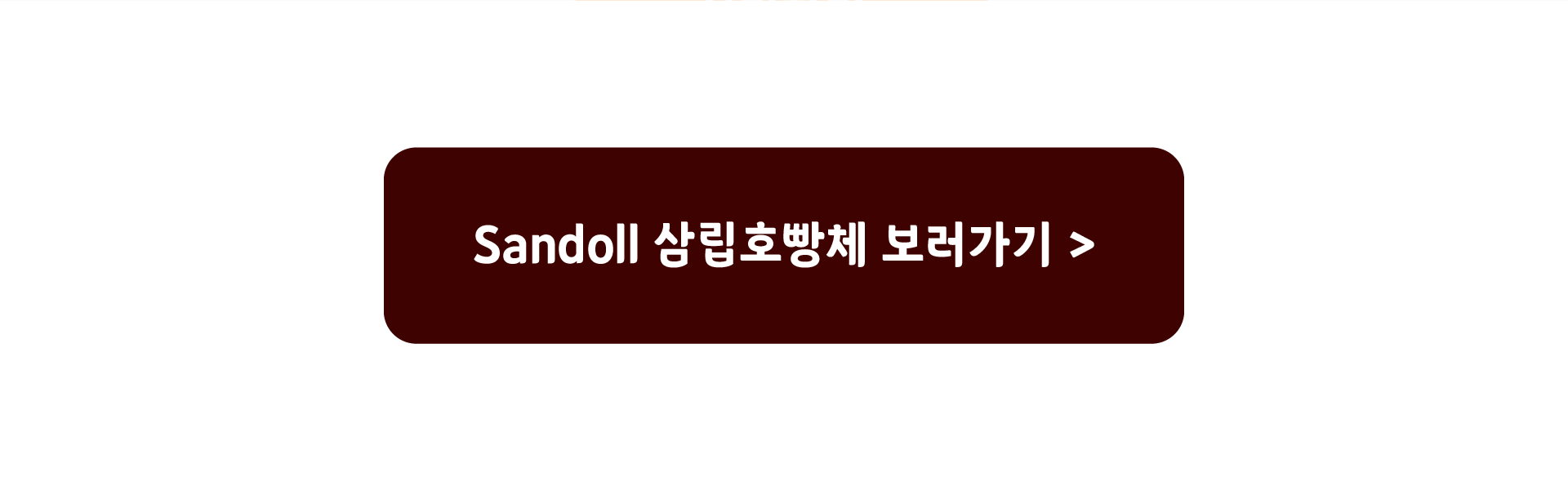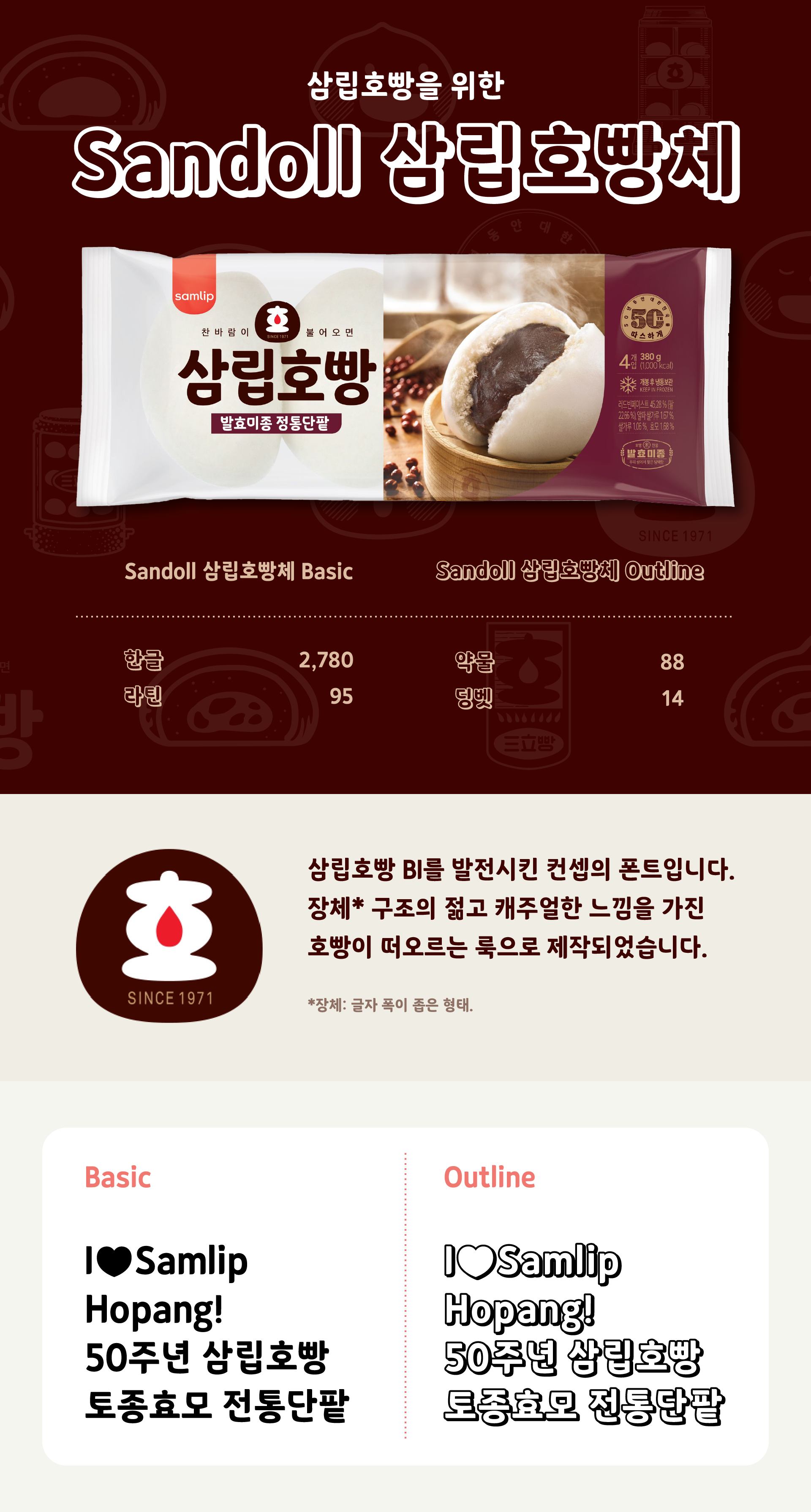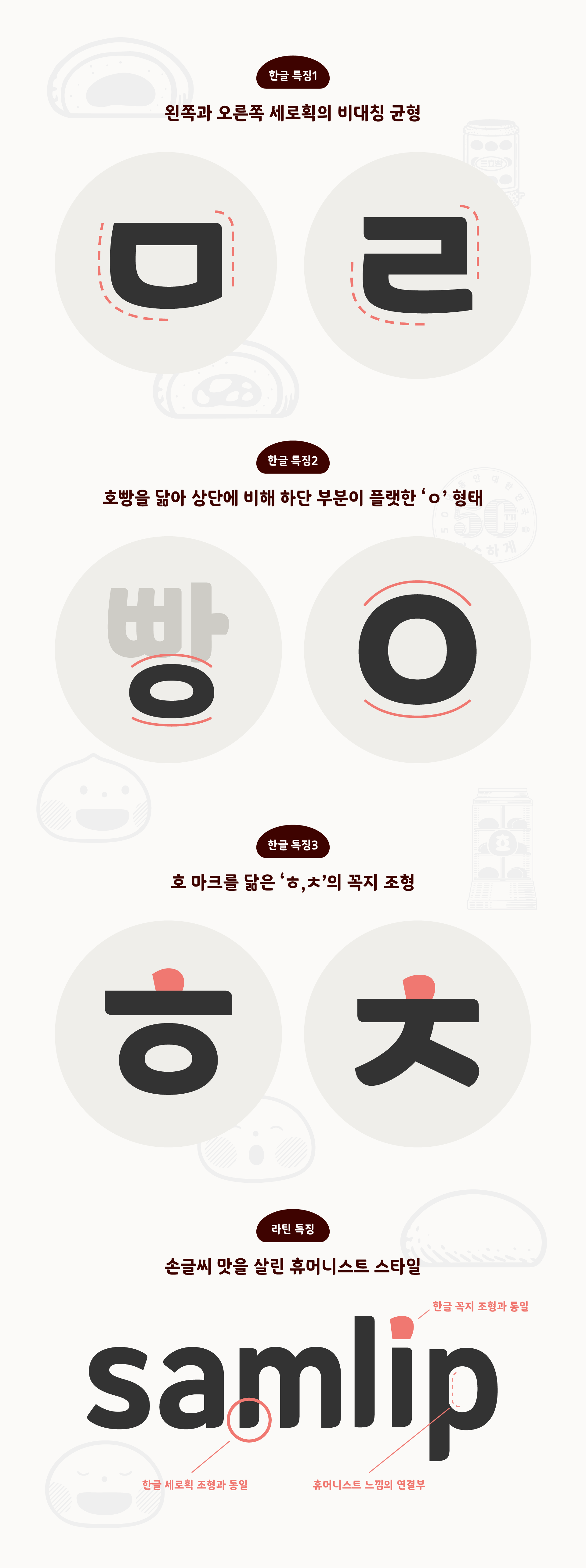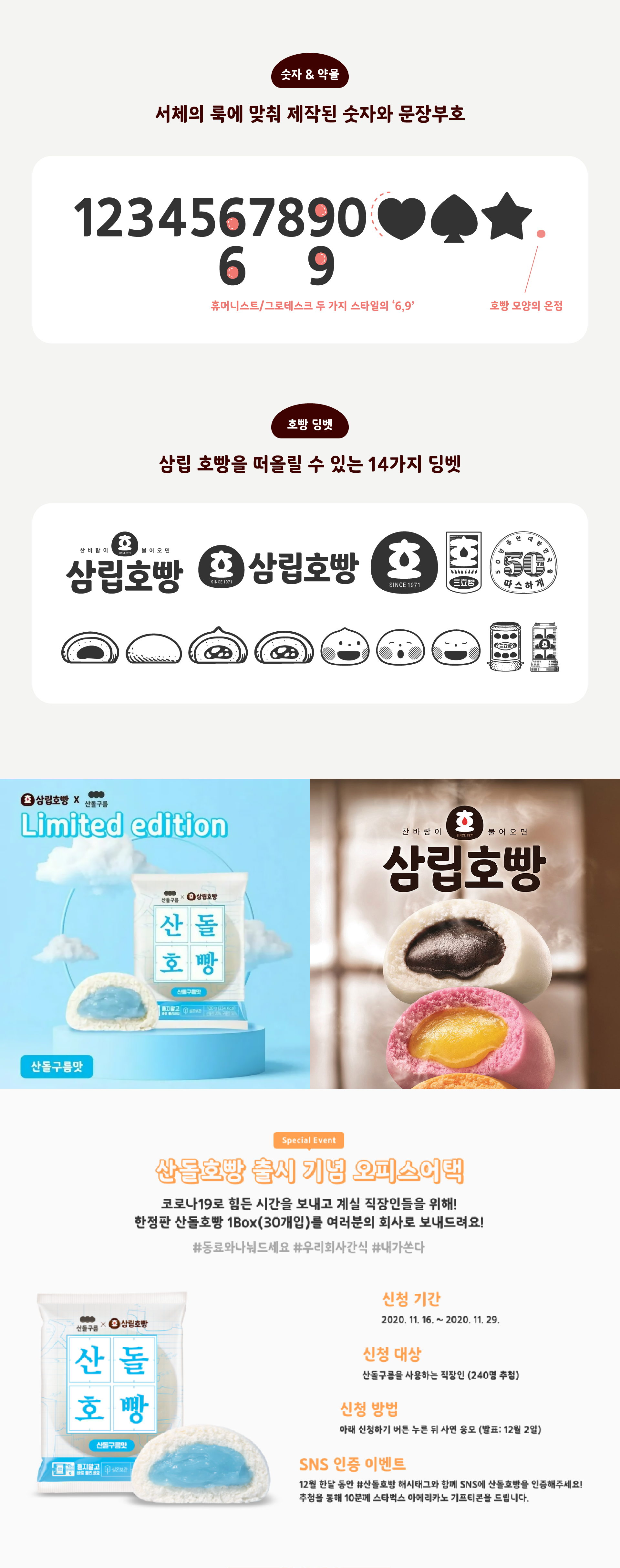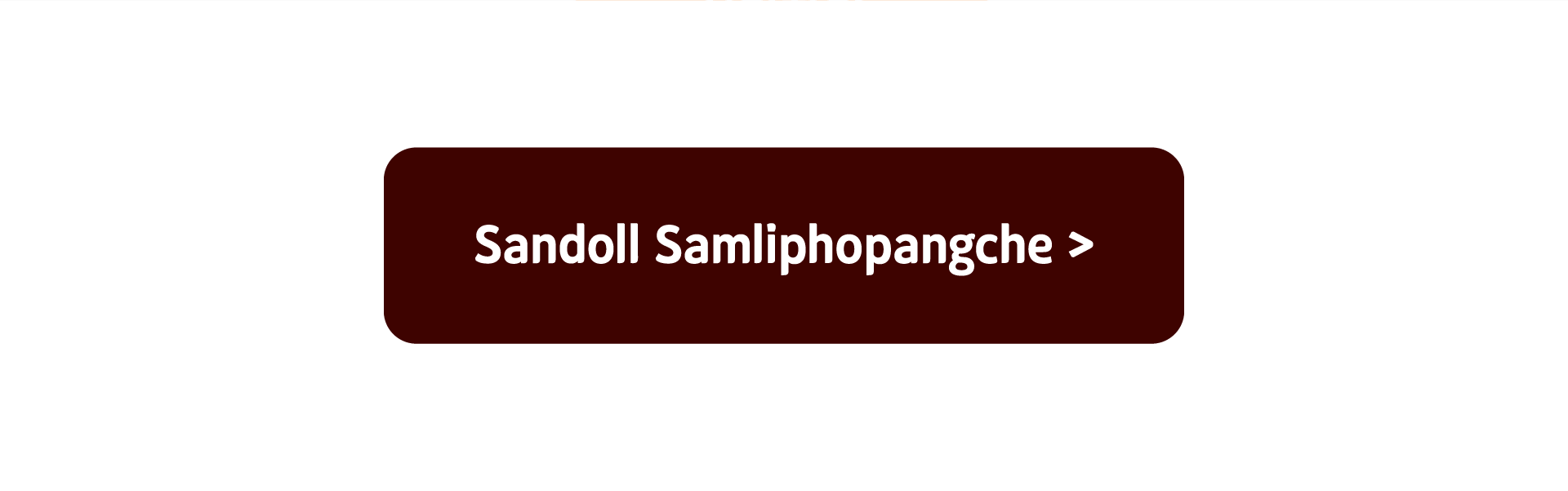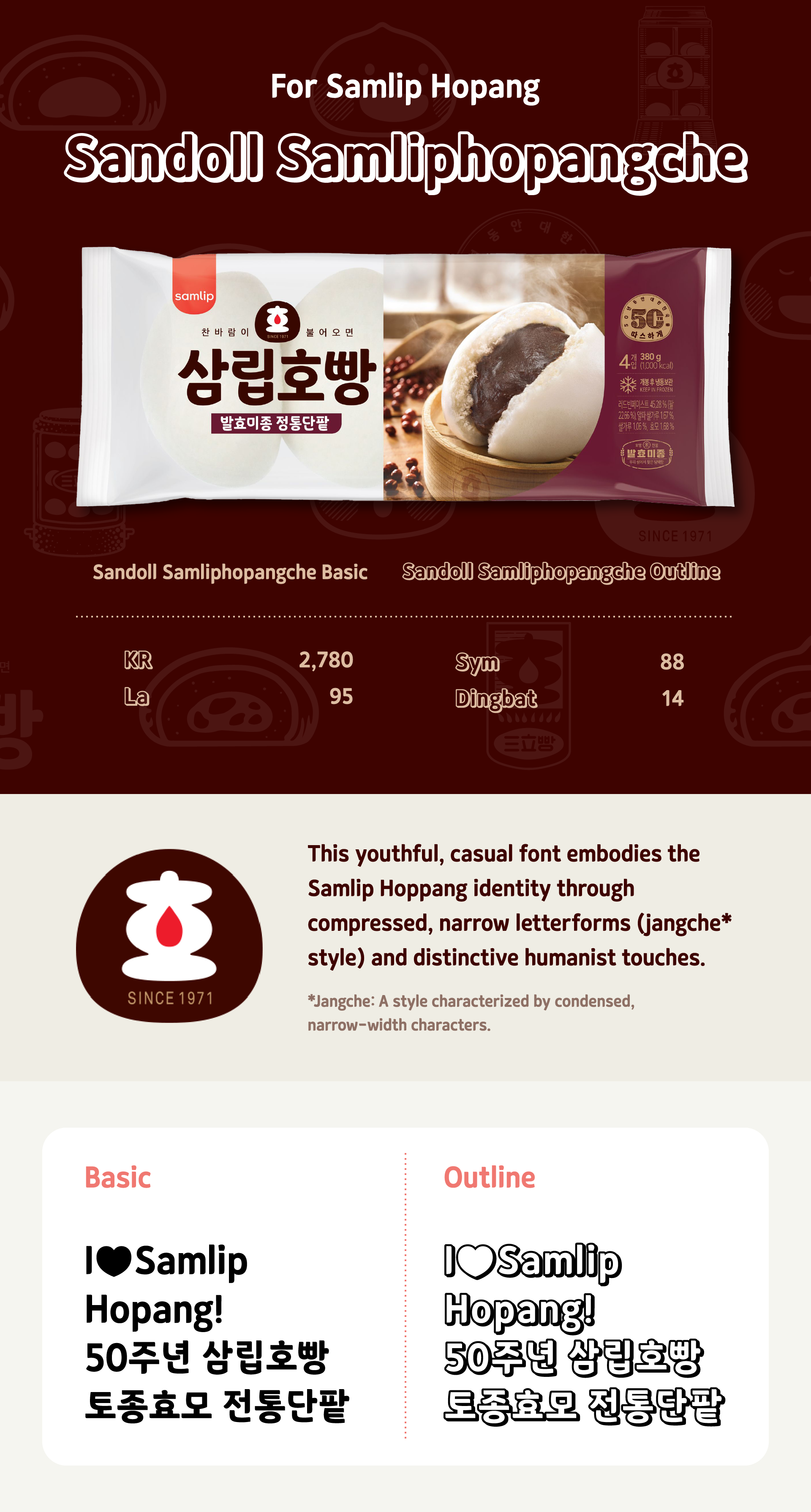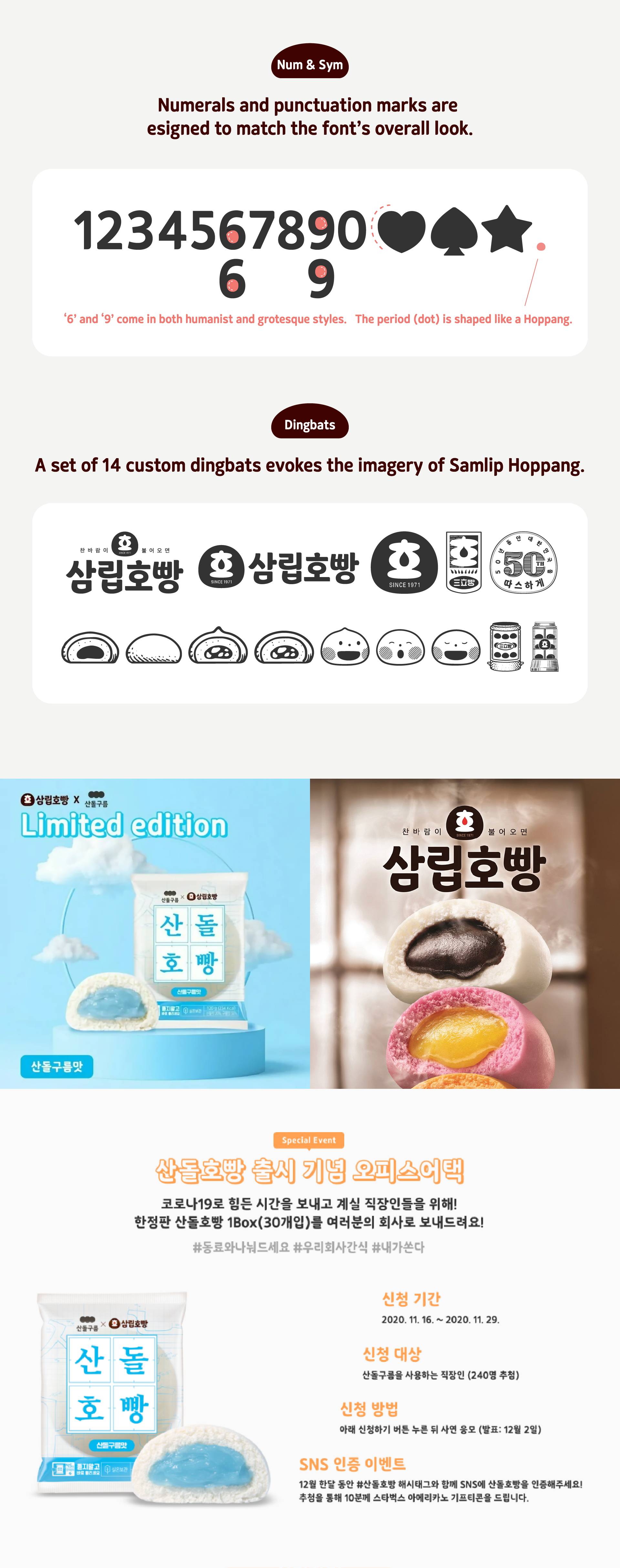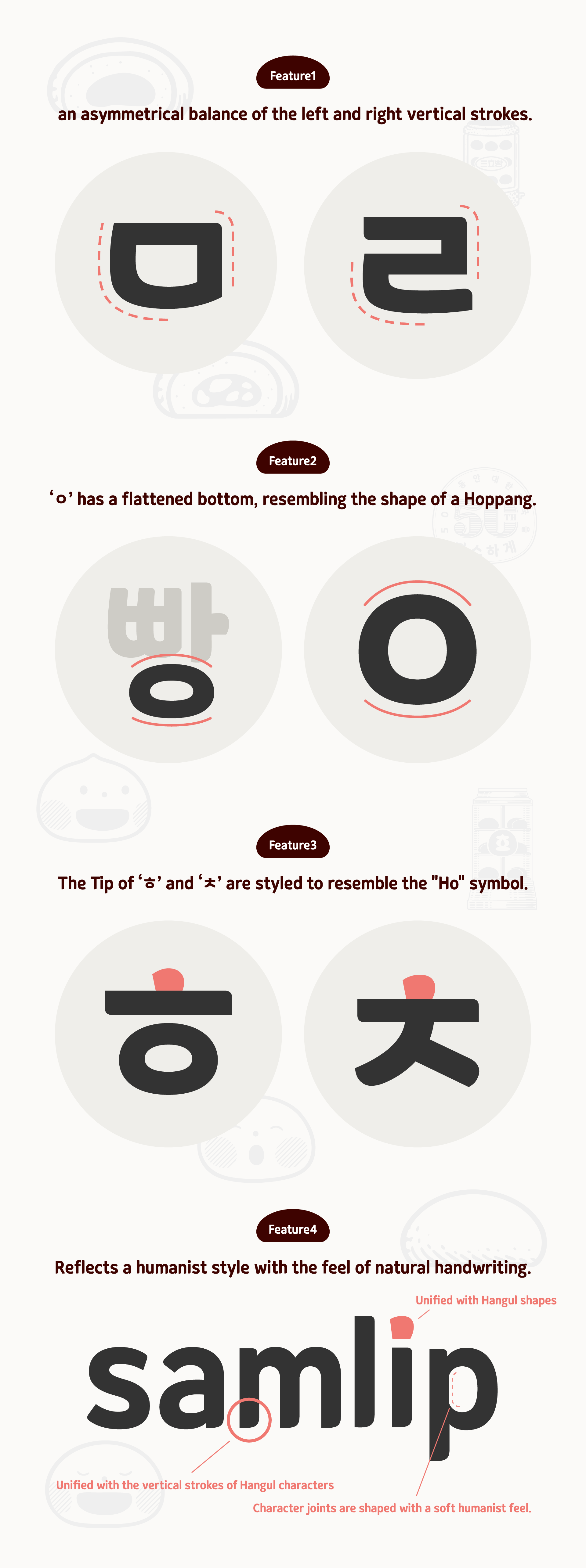
Sandoll
Samliphopangche
「Sandoll 삼립호빵체」는 기존 BI를 발전시킨 컨셉으로, 장체 구조의 젊고 캐주얼한 느낌을 가진 호호 호빵이 떠오르는 룩으로 제작이 진행되었습니다.
| Client | SPC삼립 |
| Released | 2020 |
| Classification | F&B |
| Weight | Basic, Outline |
| Teams | 강주연, 서희원 |
| Specifications | 한글 2,780 / 라틴 95 / 약물 88 / 딩벳 14 |